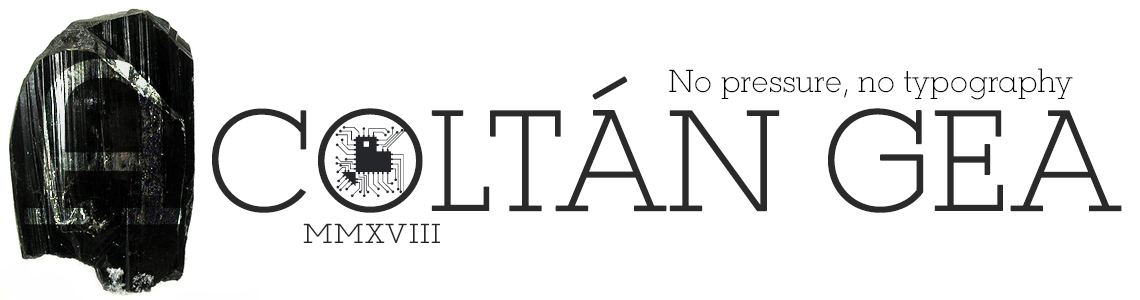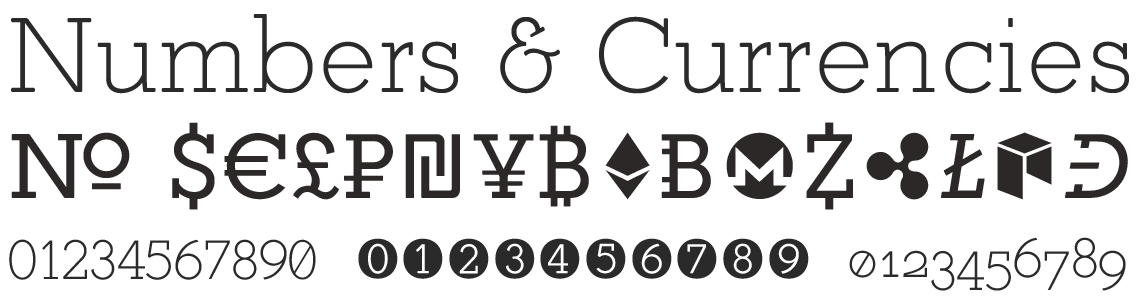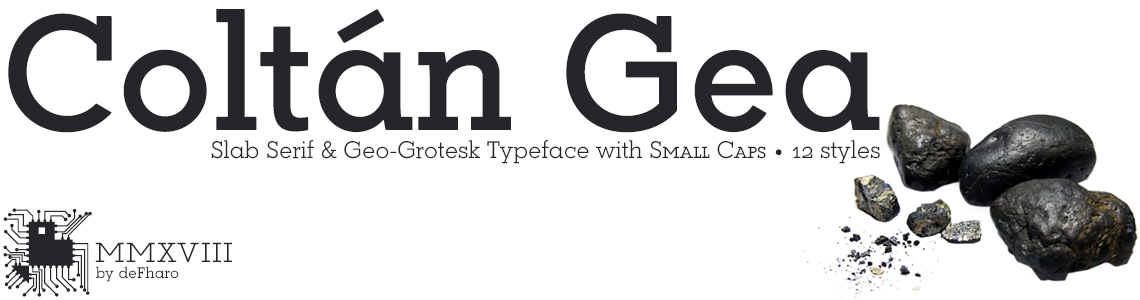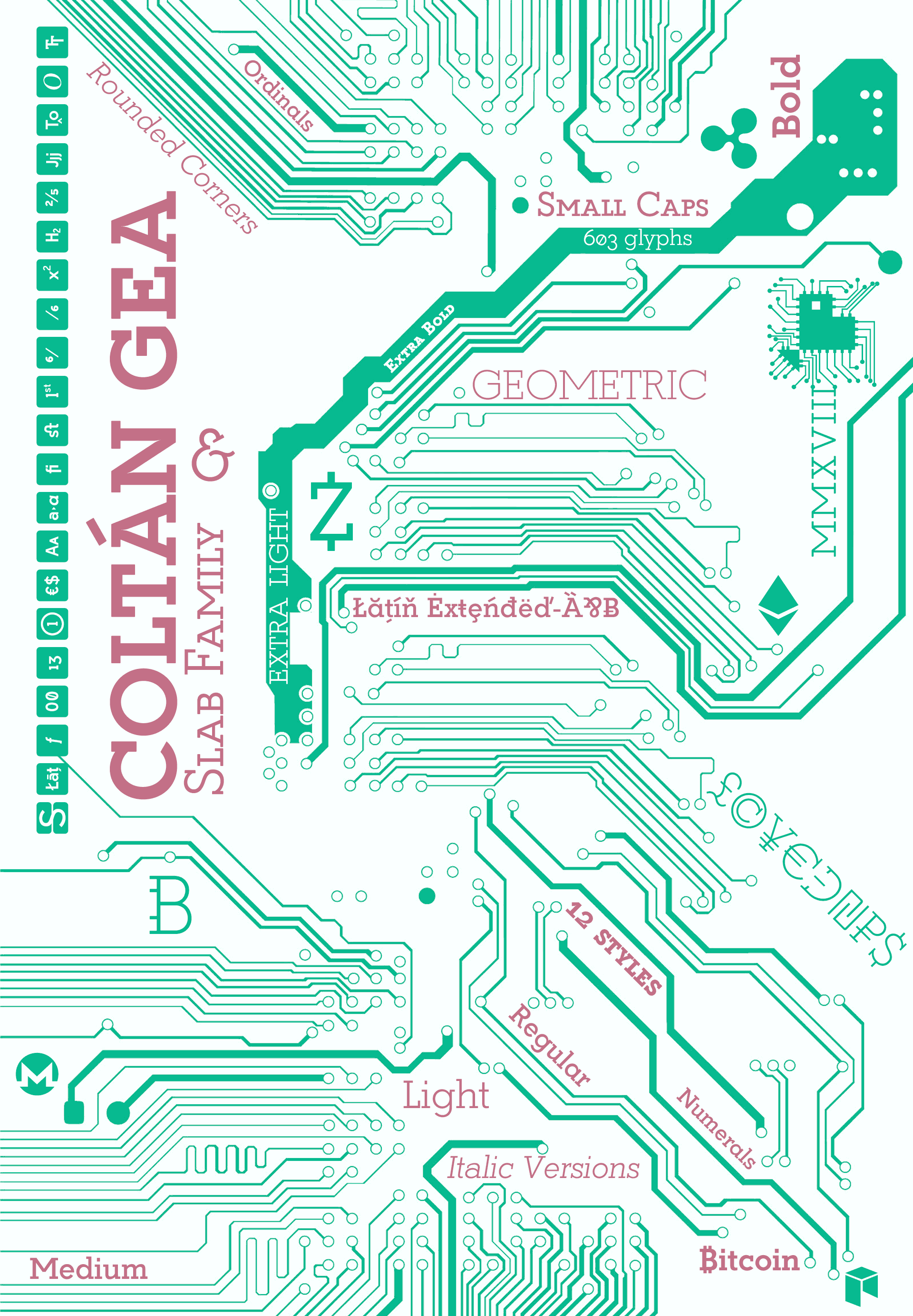
Coltan Gea – Grotesca & Slab
Coltán Gea, tipografía Slab Serif & Neo-Grotesca con Versalitas • 603 glifos
COLTÁN GEA -No pressure, no typography.
Coltan Gea Slab - Numbers & Currencies
Coltán Gea - Slab Serif & Neo-Grotesk Typeface
Coltán Gea - Slab Serif with Small Caps - 12 styles